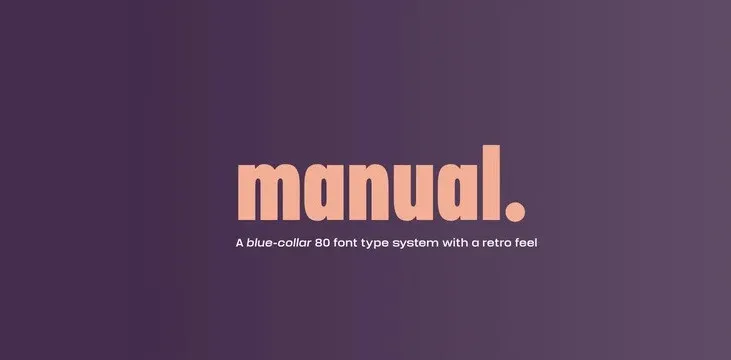
Manual Font é uma tipografia sans-serif que oferece uma experiência visual atraente para projetistas digitais. Esta família de 10 pesos formada por quatro diferentes aninhos tem um estilo geométrico e uma x-tamanho mais alta, trazendo linhas curvas retangulares com precisão e organização. O Manual exibe uma atmosfera retro suave que o faz destacar de entre outras fontes do mesmo tipo. É perfeito para trabalhos de design onde é essencial a clareza visual e a simplicidade, sendo ideal tanto para letras grandes quanto para detalhes menores. Uma fonte de trabalho duro, dedicada ao seu estilo de projeto.